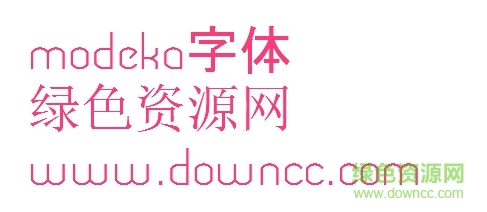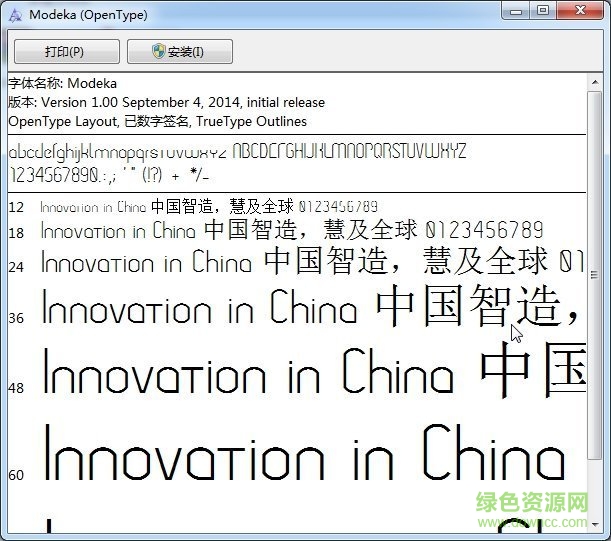
modeka是一款造型纖細(xì)的英文字體,字跡清新簡約,給你舒適的閱讀觀賞體驗(yàn),棱角分明很有象形美感,如果你在尋找modeka字體,來綠色資源網(wǎng)即可擁有哦!
Gatis Vilaks設(shè)計(jì)的Modeka是一款輕盈典雅的字體,它將角度與弧形細(xì)節(jié)結(jié)合得非常好。Modeka是一款現(xiàn)代感很強(qiáng)的藝術(shù)字體,在藝術(shù)設(shè)計(jì)中能為你的文字內(nèi)容增加光彩!